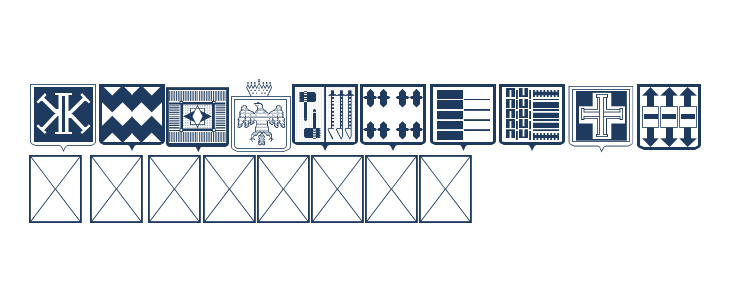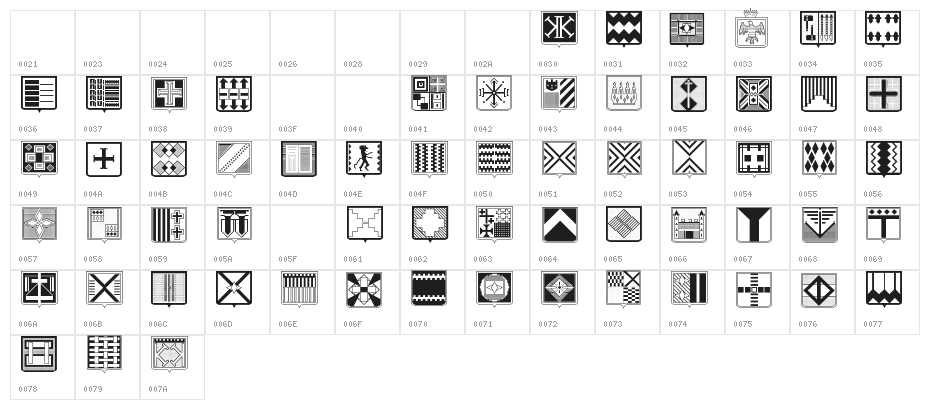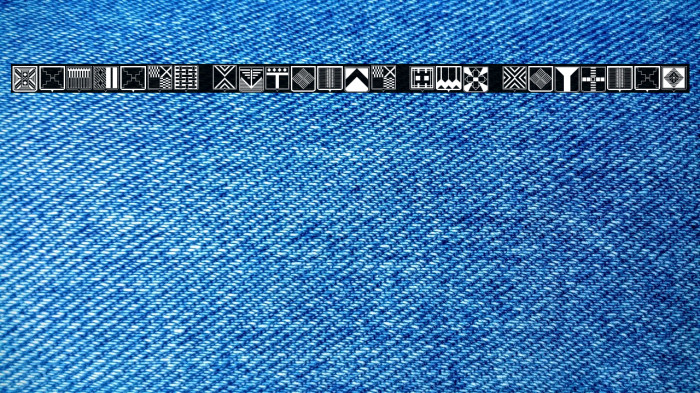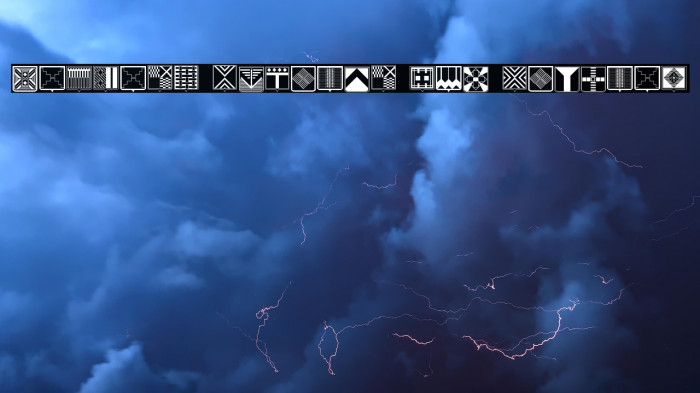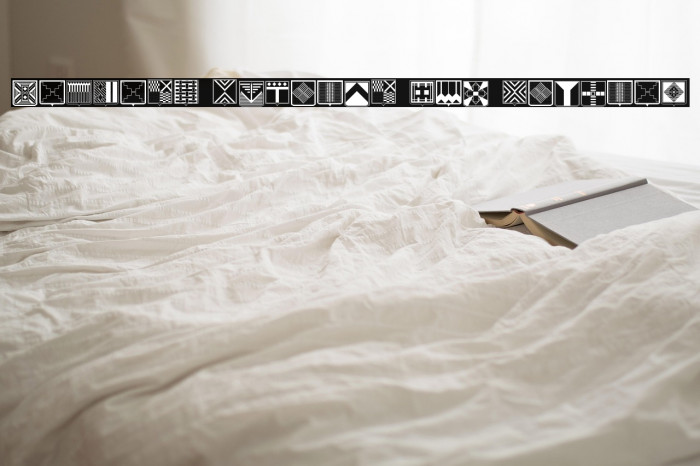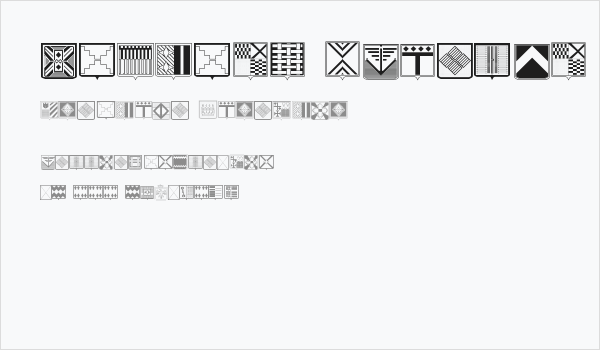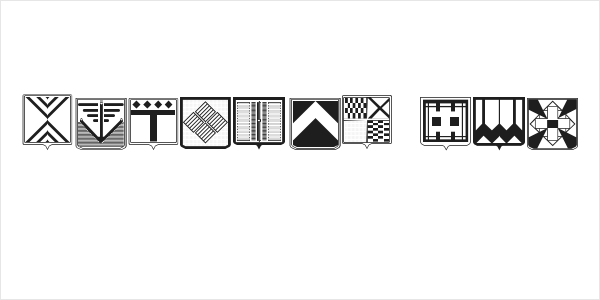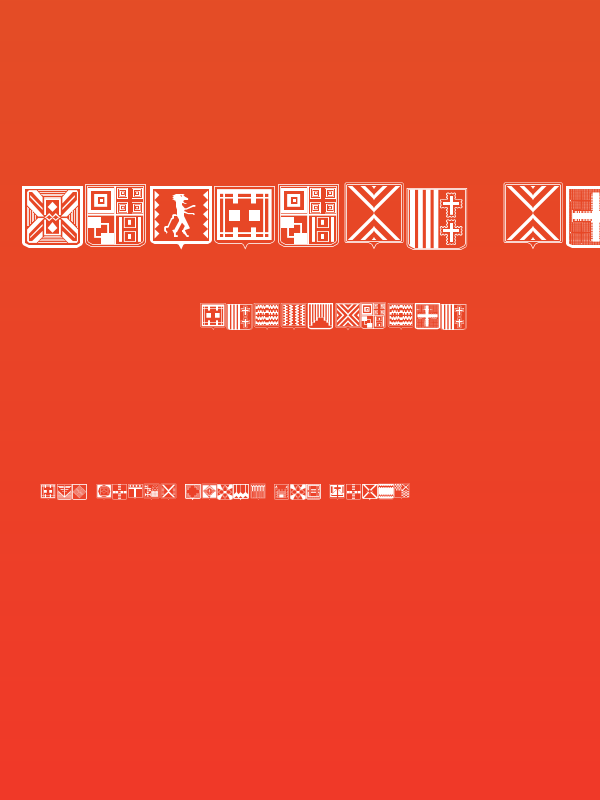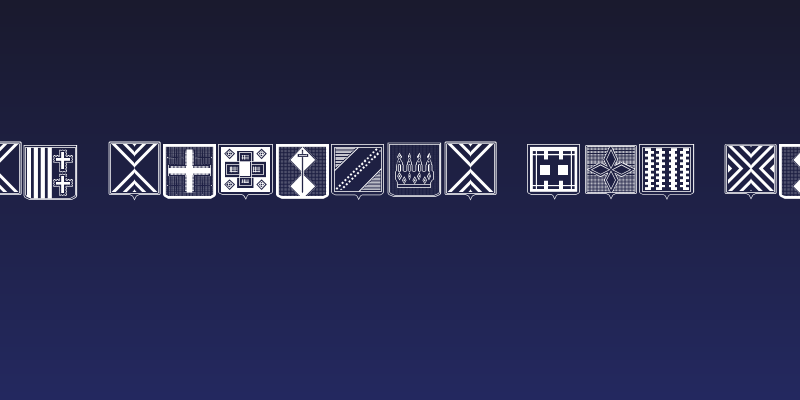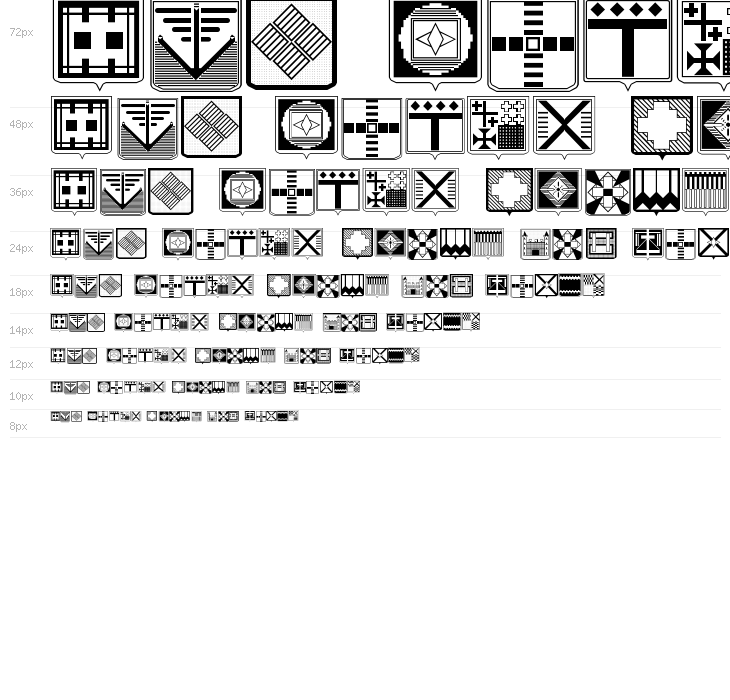
Fantasy Shields Two Regular Font
| Stil general | Decorative, Fantasy, Heraldic |
| Caz de utilizare | Logos, Icons, Themed graphics, Decorative initials |
| Proiecte propuse | Game design, fantasy book covers, RPG maps, heraldic posters, themed invitations, branding for fantasy events. |